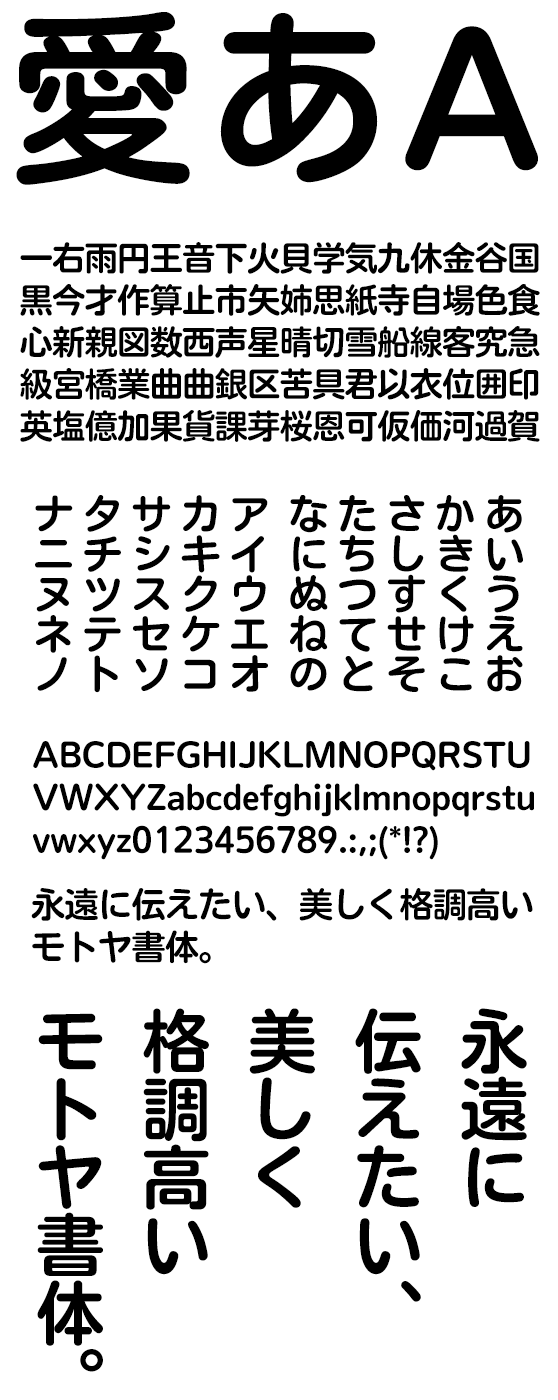
丸ゴシック
NUDモトヤマルベリ5 LiteN
NudMotoyaMaruLiteN-W5
充分な丸みを持ちながら、かつシーダの特徴であるスッキリとしたイメージを併せ持った、シーダの丸ゴシック版と言える書体です。
モトヤUDフォントは、大文字化対応や太さの調整、シンプルな文字構成で通常のフォントより可読性・視認性・判読性に優れており、医療分野/組込み機器表示/各種パッケージでの利用に最適です。